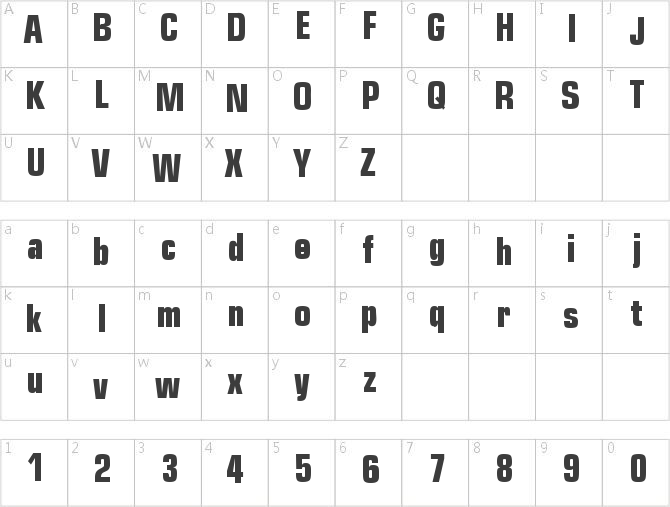
EurasiaCond 詳情頁(yè)
字體名稱(chēng): Eurasia
EurasiaCond字體字庫(kù)是一款讓人賞心悅目、百看不厭的英文字體,適合各類(lèi)廣告和產(chǎn)品包裝設(shè)計(jì)應(yīng)用,字體大小0.04MB,格式為ttf字體,上傳用戶(hù)是123123aaa,作者/版權(quán)方為未知